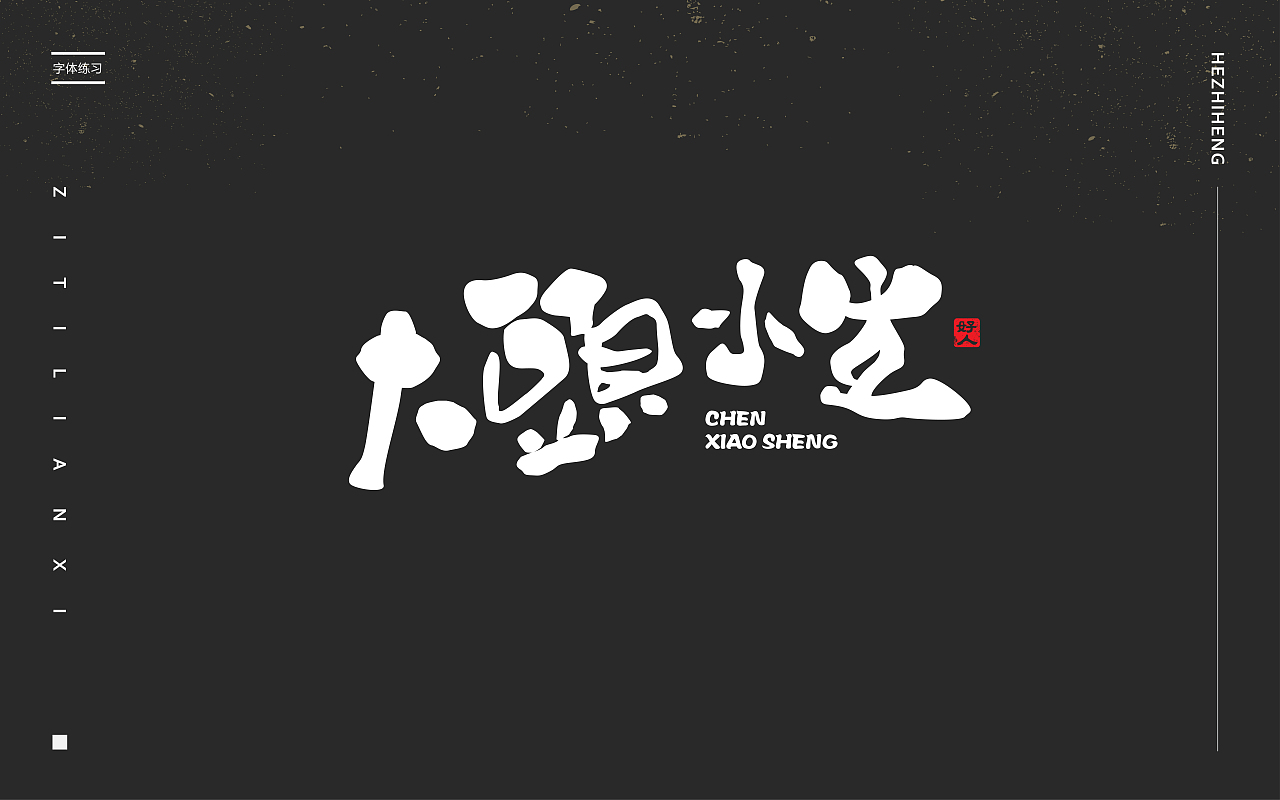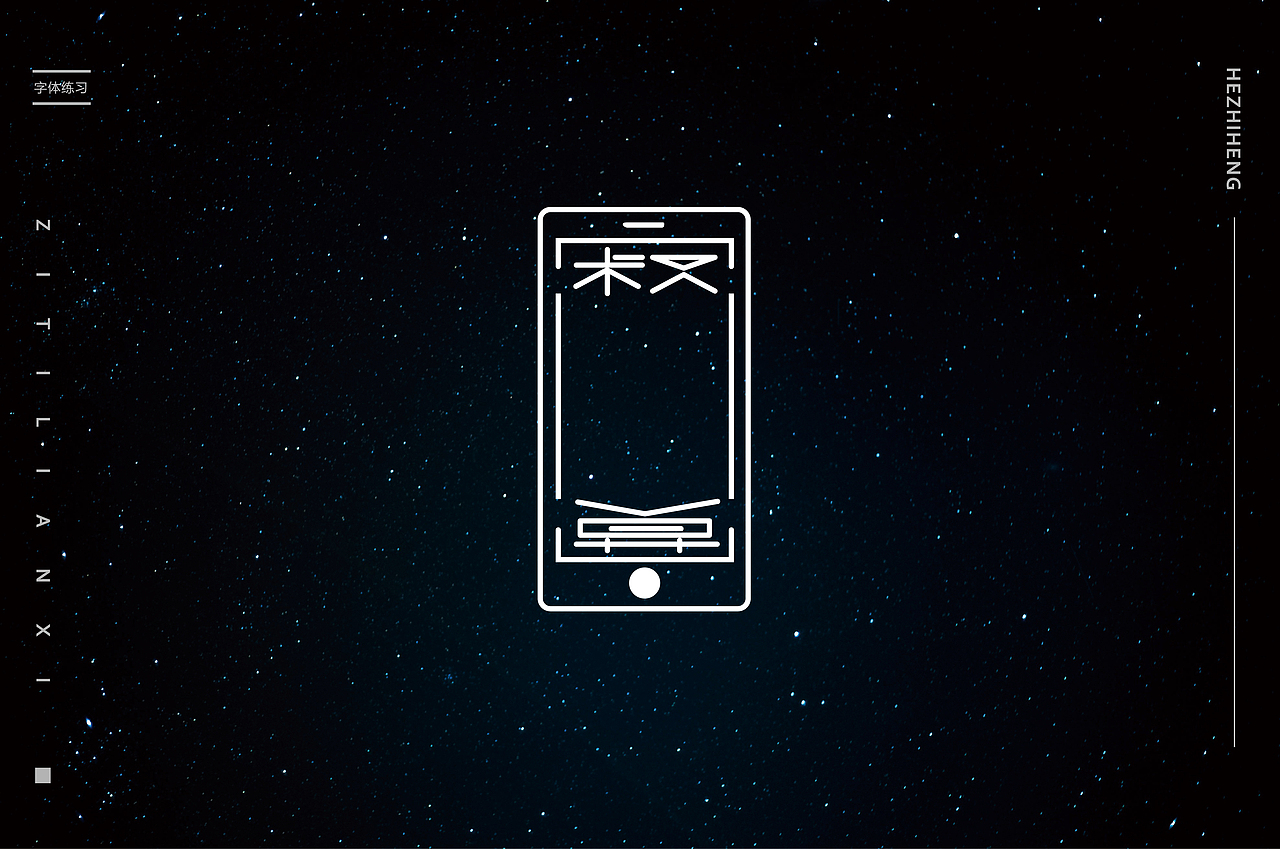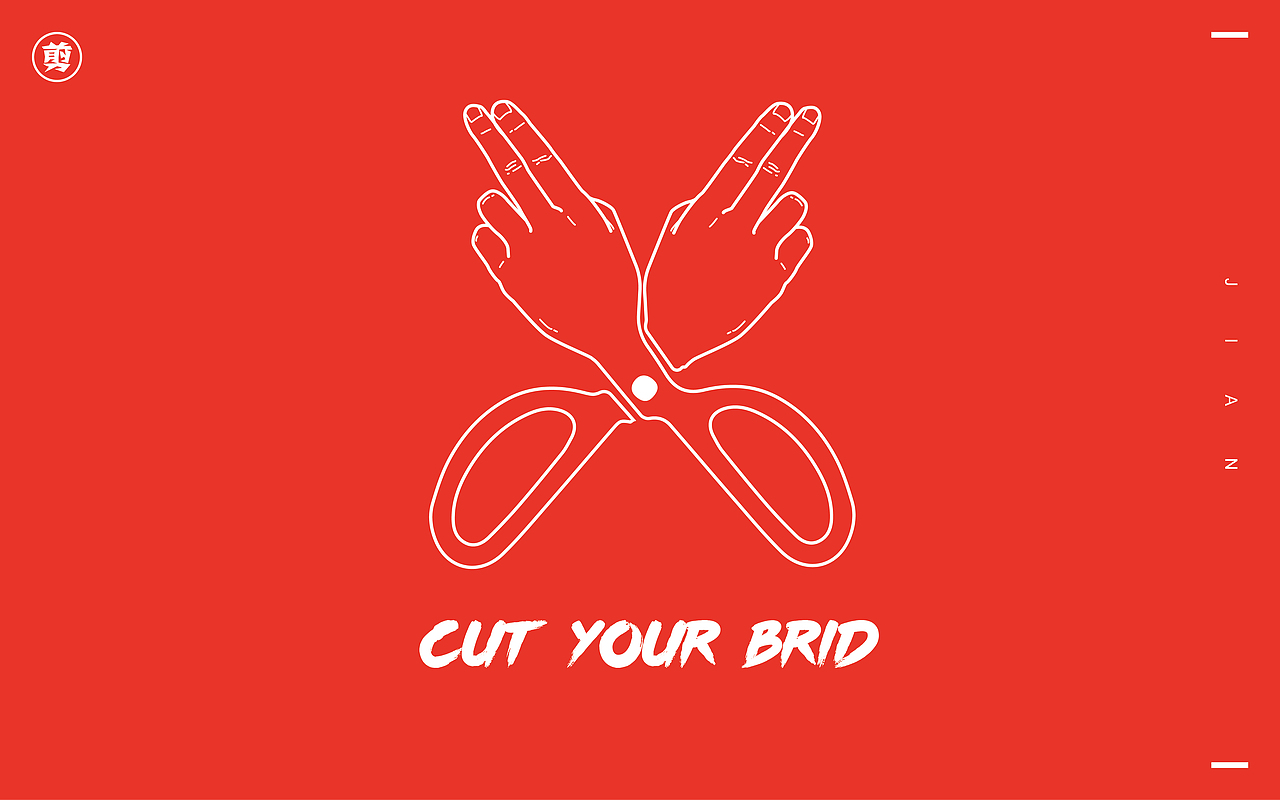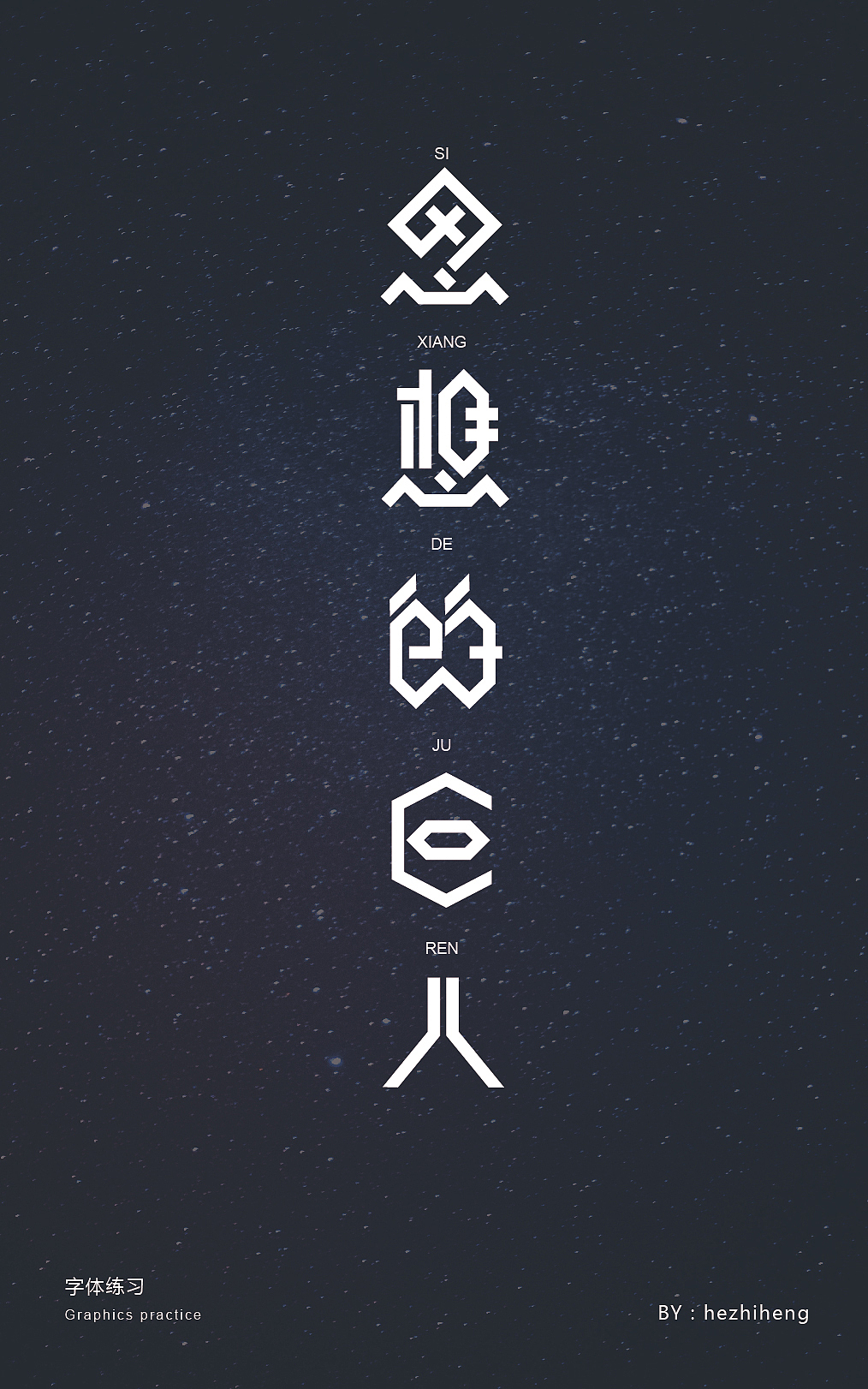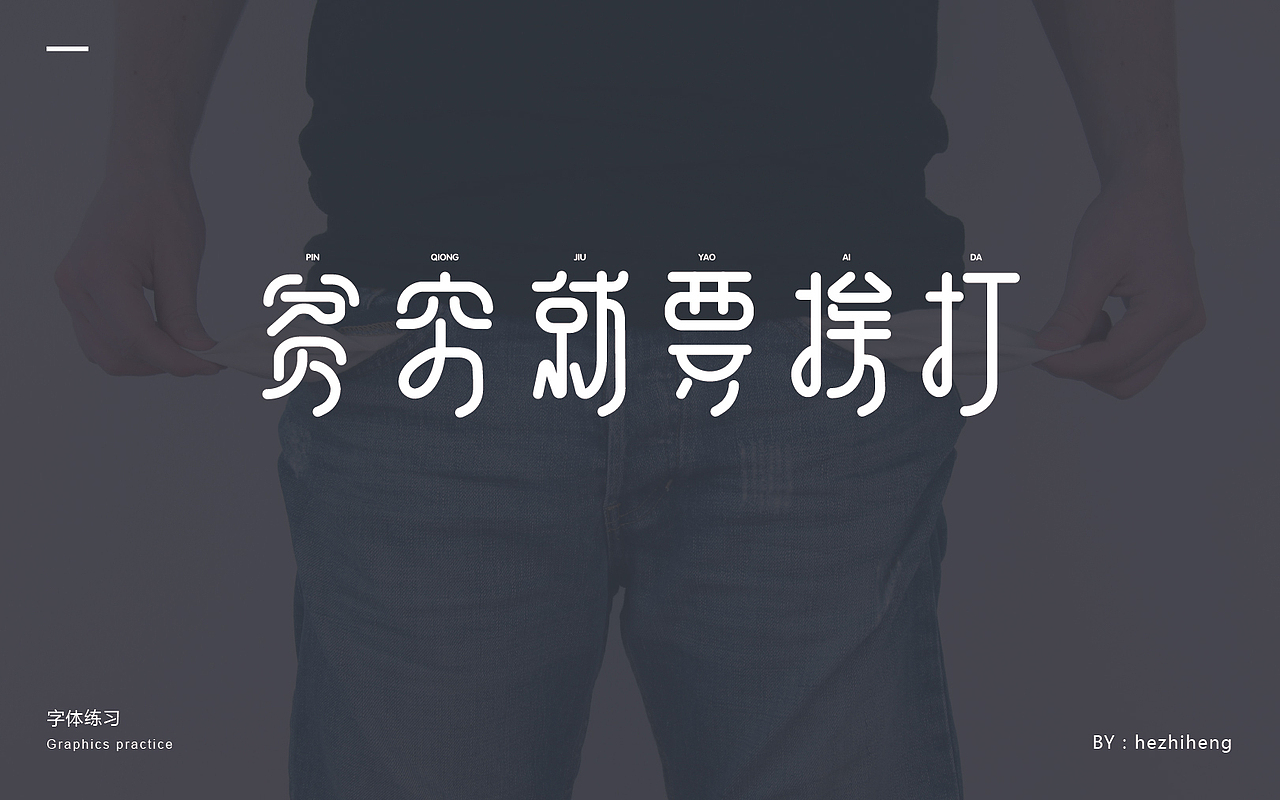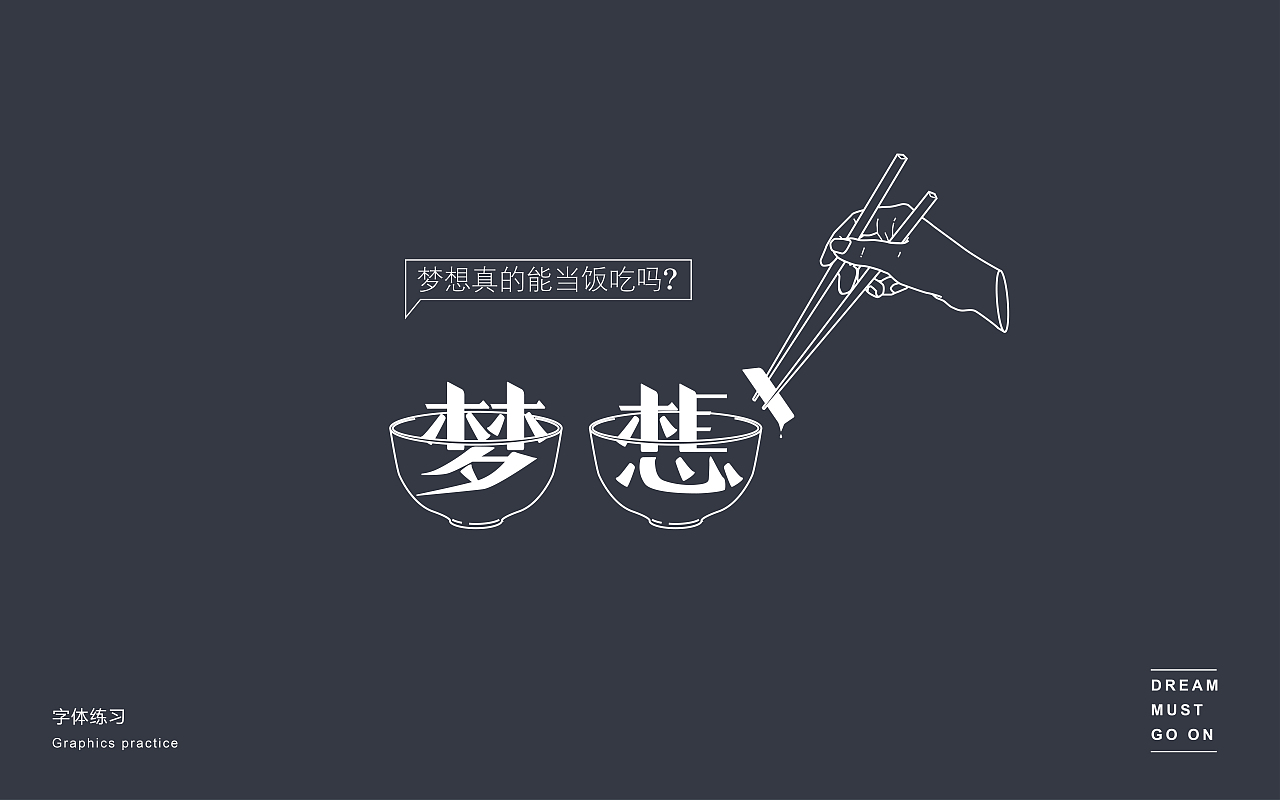
城市好大,心好小
拿着不包吃住月薪2.5K在深圳待了半年,终于熬不下去,在将要离职之际整理了一下这段时间的设计练习
(周末根据站酷 @张家佳 老师的教程,做的小练习,肯定没老师做的好,但仍在努力! )
大学时候的花名,这算是第二次尝试做字体设计吧(第一次是毕业设计时候),那段时间公司没什么单,就做着玩,想不到越做越觉得字体设计好玩。
大学一个非常好的同学
每晚凌晨回到400一个月的农民房,一个人面对这十平方不到的房间,却感到无比的空荡荡,拿起手机想找个人聊天,却不知道找谁。
一个跟我玩得很好的大学同学鲁美,那段时间她刚到新公司上班,看着她当时的微信头像,忍不住拿来做了这张海报。
一直都好喜欢 @石昌鸿 老师的作品,从他的字体作品中得到的灵感启发
谢谢鲁美当时给我的想法,这一双加藤鹰的手刺激了我之后的那些创作
这张是送给一个为了寻求真爱而漂洋过海的高中同学,祝你早日找到幸福。
习惯性的拖粮已经让我考虑到活着的意义,半年了,每个月都拖十多天,早已经人脉透支的我,饥寒交加只能不断给自己灌鸡汤,鼓励自己自己选择的路跪着也要走完。
已经到了没有脸再开口叫朋友借钱的地步了,坐在办公室里面听着外面的老板演讲式地向客户说着品牌的力量!梦想的意义!成功的方法!他所说的台词我基本都能背下来了,我默默地打开钱包,只剩下7毛钱。
把梦想吃完后,我退化成一条咸鱼。晚上我厚着脸皮叫朋友借了50块请了招我进来的总监吃宵夜,一瓶啤酒下肚跟他提出了辞职。